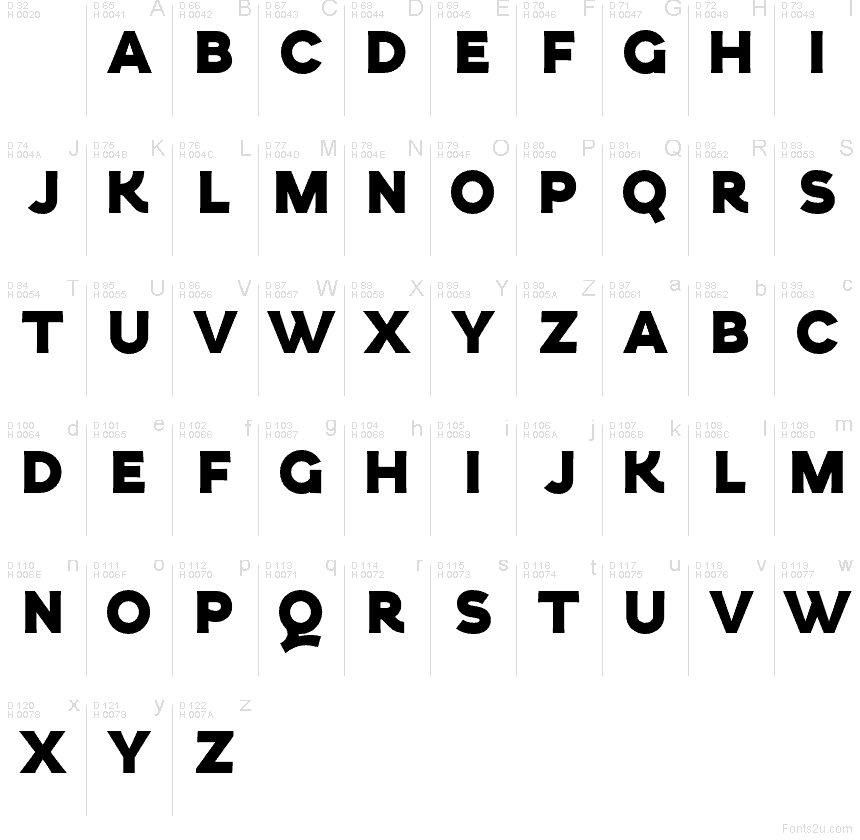
Typolio Regular
Typolio je bezplatné bezpätkové písmo definované širokou, blokovou siluetou a výraznými hranatými rezmi, ktoré dodávajú literám silnú, plagátovú prítomnosť. Vďaka okrúhlemu O a kompaktným vnútorným tvarom hmota nepôsobí neohrabané, takže dizajn vyznieva zámerne a graficky, nie len ako zväčšenina.
Tento typ hutného obrysu sa skvele hodí na obaly albumov, firemné nápisy, športovú grafiku, obaly a titulky, kde krátke slová potrebujú pevnú vizuálnu úlohu. Typolio môže tiež ukotviť návrhy log a hlavičky pre sociálne siete, najmä ak hľadáte jednoduché bezpätkové tvary, ktoré pôsobia vážne, priamočiaro a ľahko sa kombinujú s čistejším doplňujúcim textom.